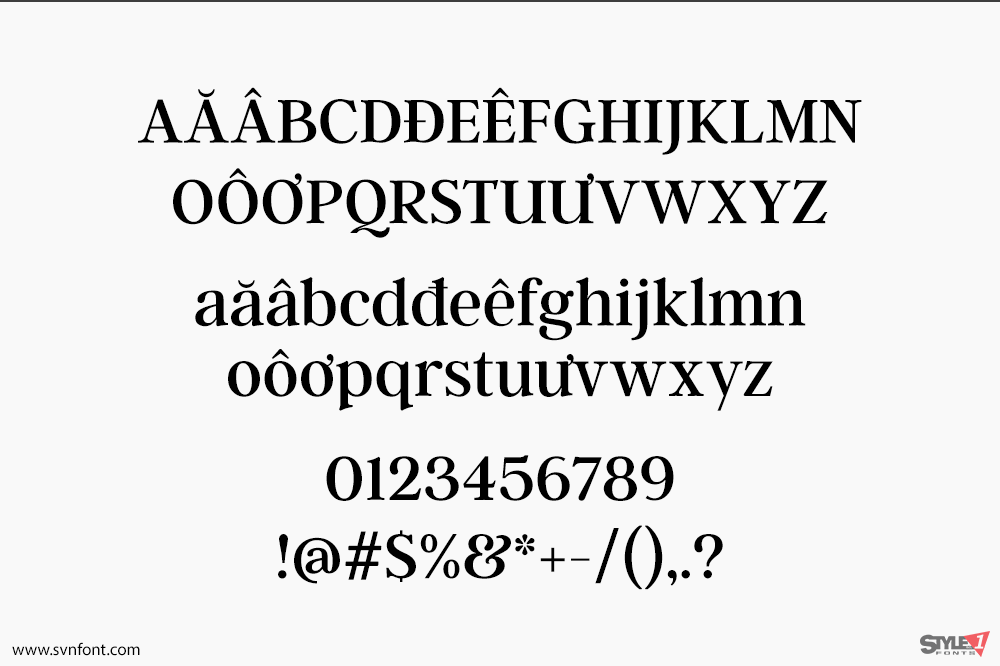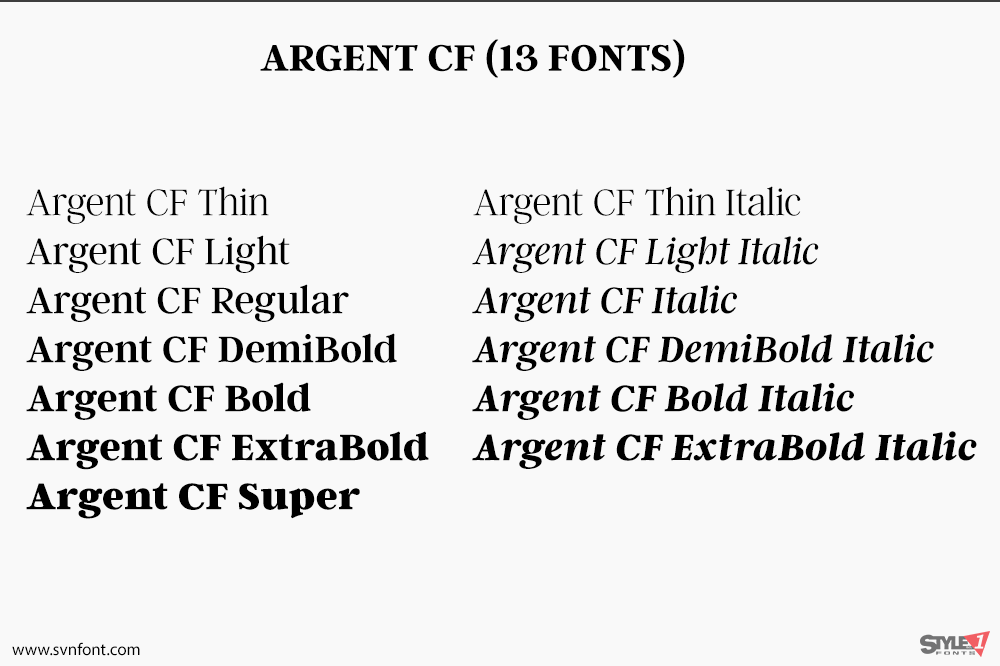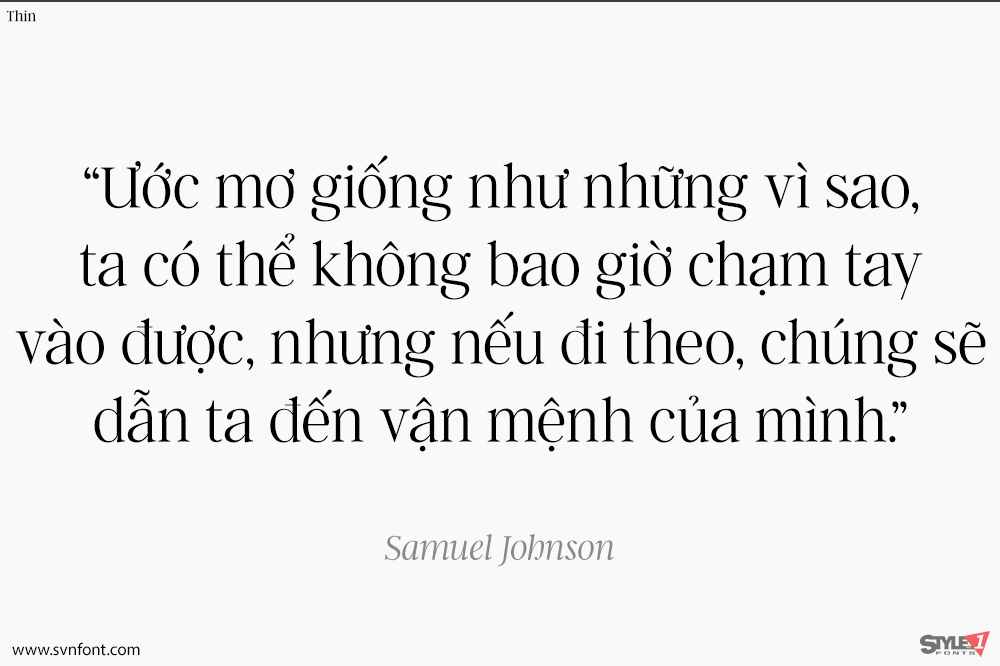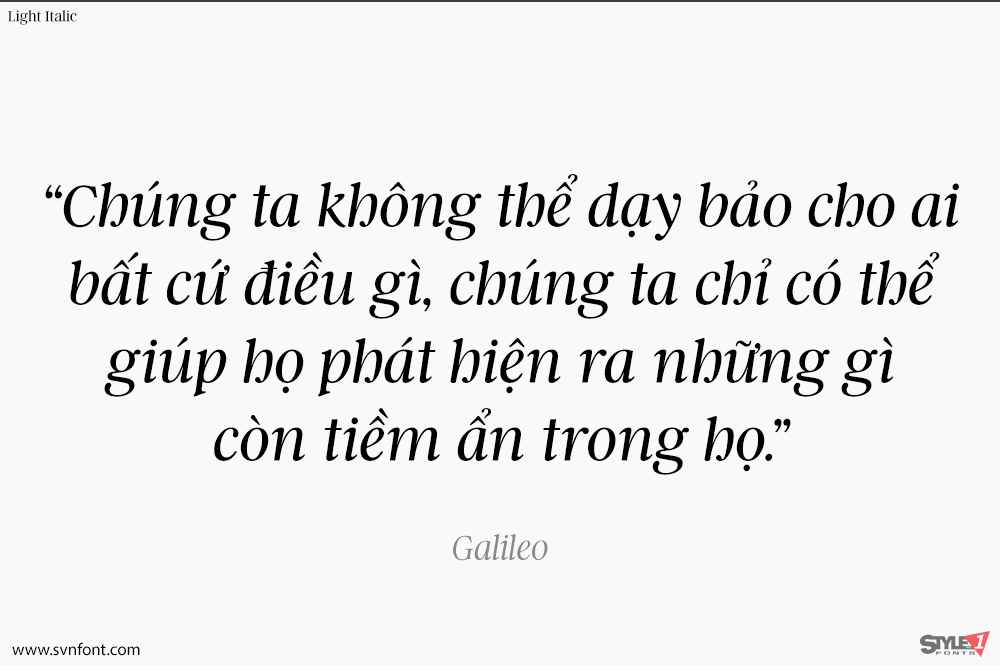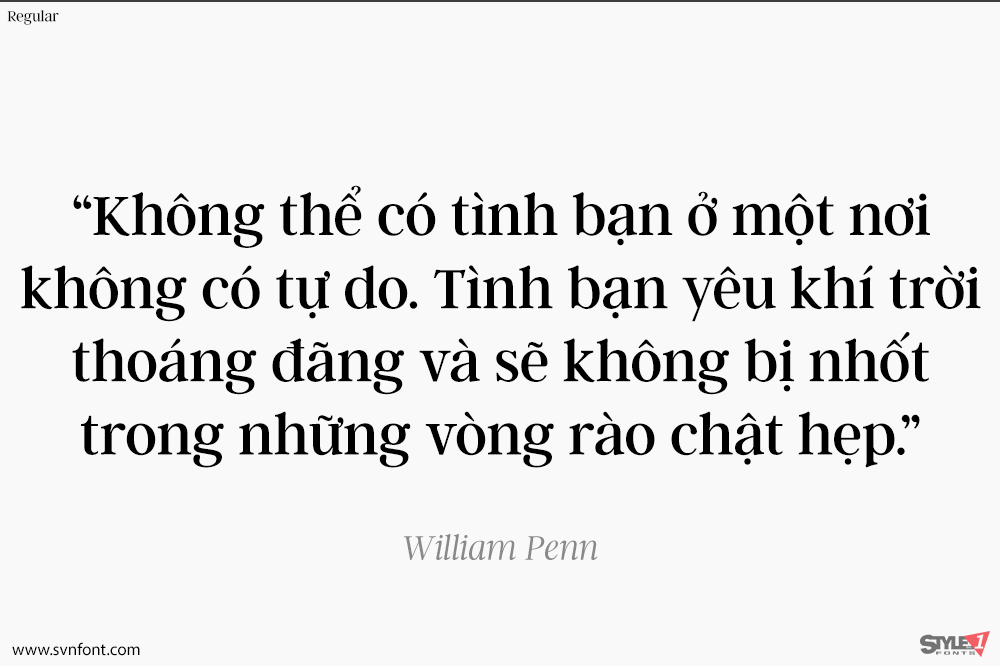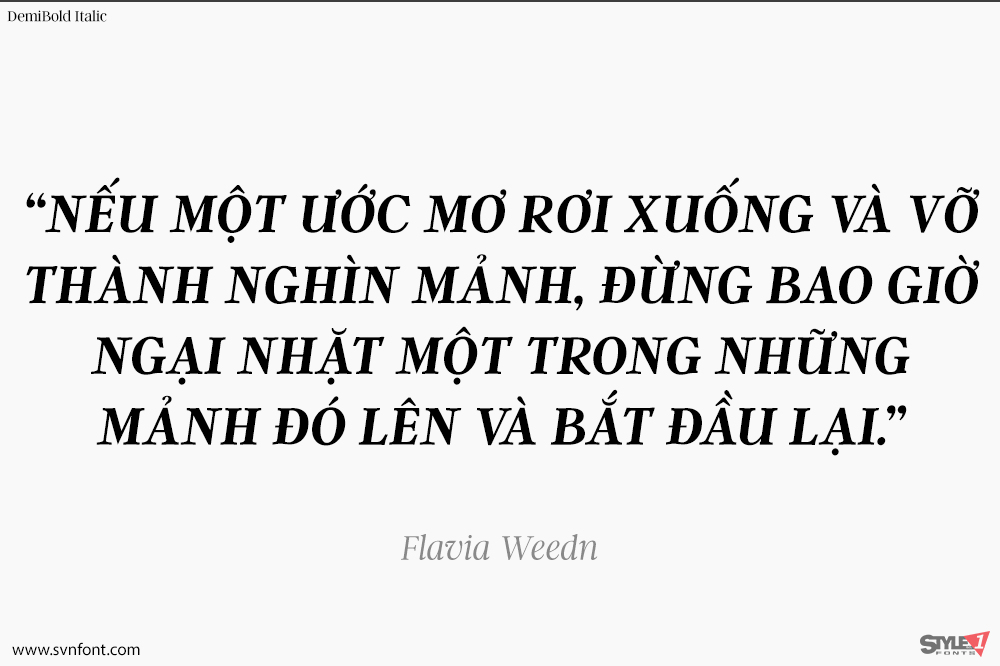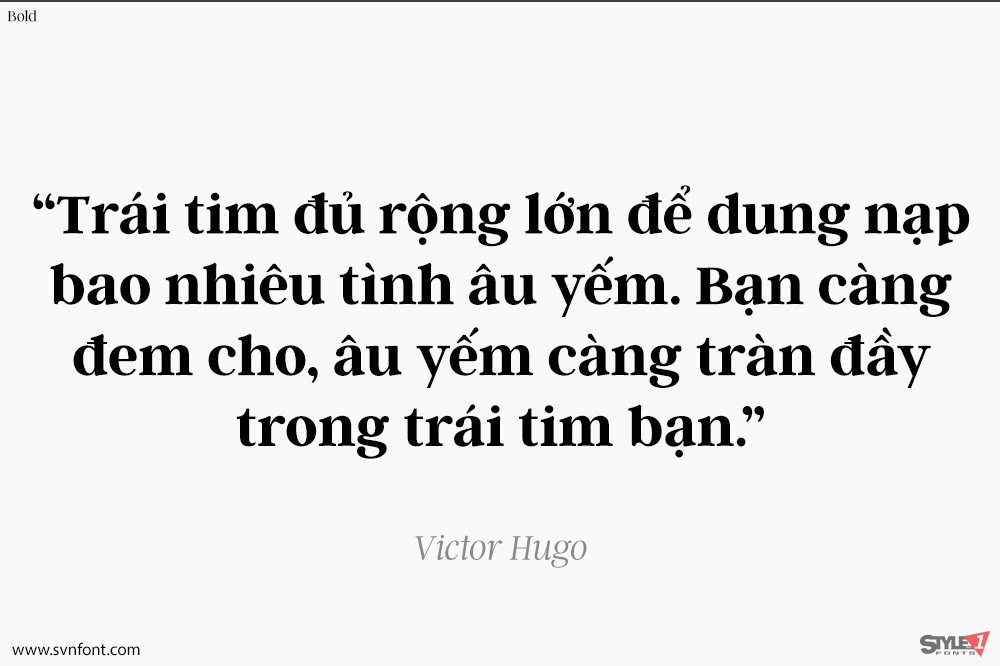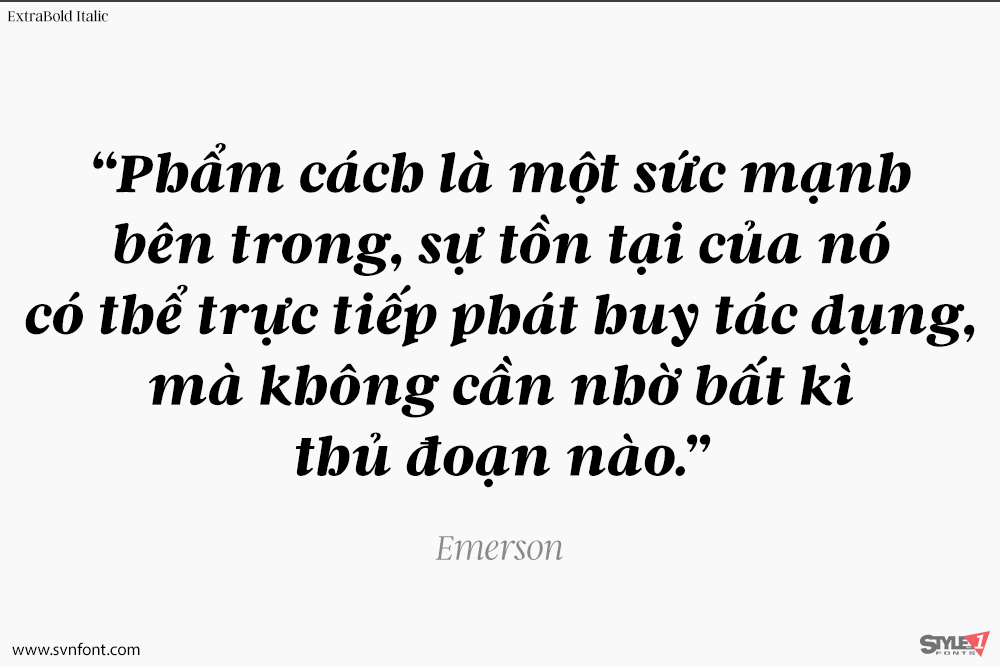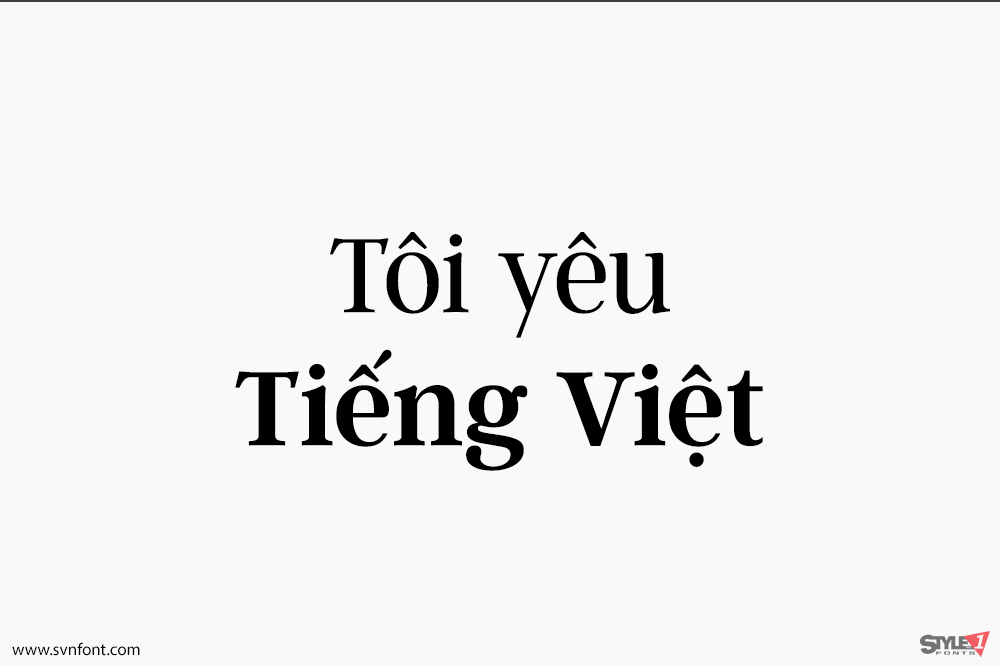
Argent CF là một phông chữ lộng lẫy và biểu cảm, với chiều cao x-height nổi bật cùng các hình dạng chữ gợi cảm và uyển chuyển. Với các kiểu chữ nghiêng duyên dáng, một độ đậm siêu đậm đặc biệt (superbold weight) và hỗ trợ ngôn ngữ rộng, Argent rất xuất sắc trong các cài đặt hiển thị như tiêu đề chính, tiêu đề phụ và logo. Là một kiểu chữ biểu cảm và chi tiết, Argent kết hợp rất tốt với các phông chữ sạch sẽ, tạo sự tương phản, chẳng hạn như các phông sans serif như Greycliff CF, Artifex Hand CF và Articulat CF.
Designers: Connary Fagen
Publisher: Connary Fagen